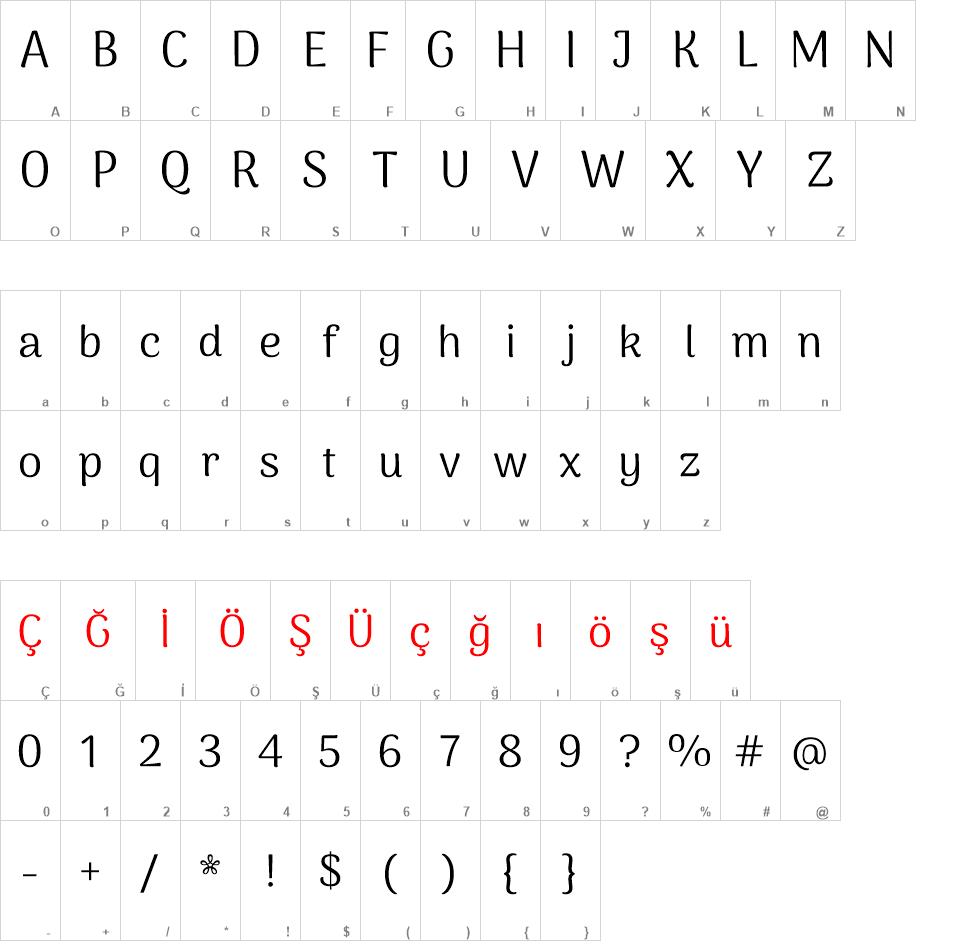
Arima Madurai
Arima Madurai font
Die Inspirationsquelle für das Arima-Projekt ist eine weichkantige und kalligrafische Schrift.
Der Kontrast ist gering, um eine gute Darstellung auf dem Bildschirm zu ermöglichen. Lesbarkeit ist immer ein zentrales Anliegen, aber es hat viel Persönlichkeit, um als Bildschirmschriftart erkannt zu werden, die in Design, Titel, Markennamen und ähnlichen Anwendungen im Web verwendet wird. Das Hauptziel bestand darin, ein Design zu schaffen, das sich bei gewöhnlichen und professionellen Designern als beliebt herausstellt und die Qualität des Designs anspricht. Jede Schriftart der Familie wurde ausgiebig an Handys mit niedriger Auflösung getestet und als mobile Schriftart im mobilen Zeitalter optimiert. Seit der ersten Entwurfsrunde wurde jede Schriftart von ttfautohint impliziert und für Windows-Benutzer verfeinert.
Arima Madurai bietet umfangreiche Sprachunterstützung für tamilische und lateinische Schriften.